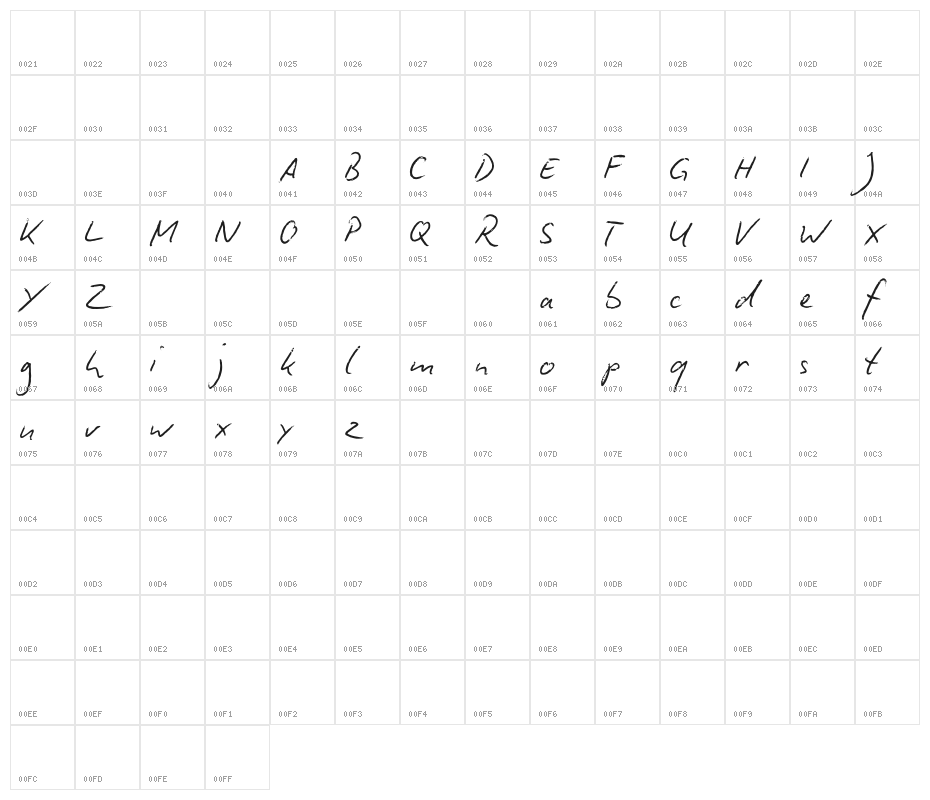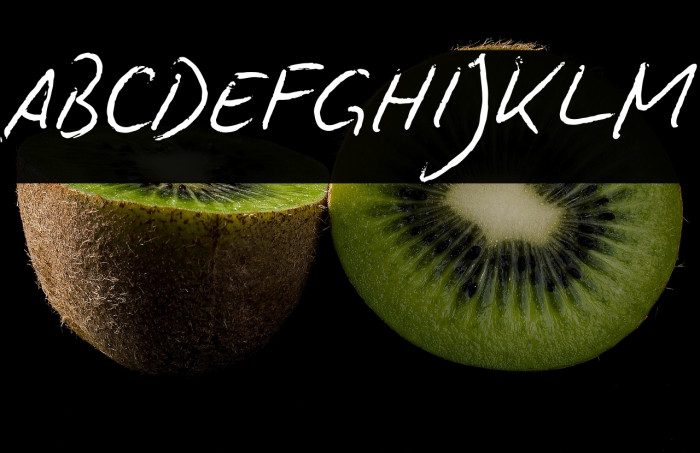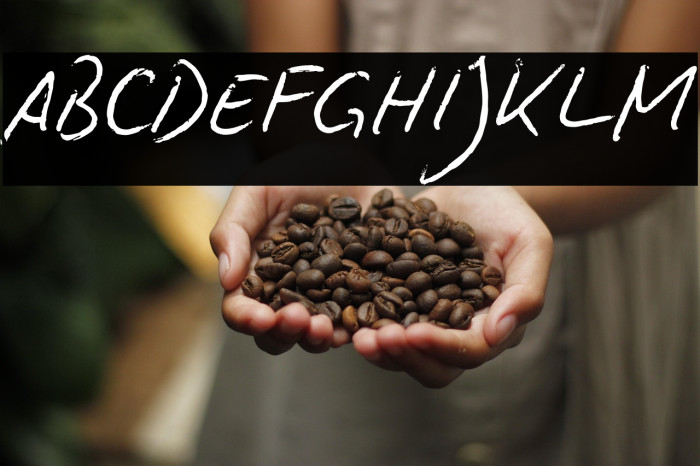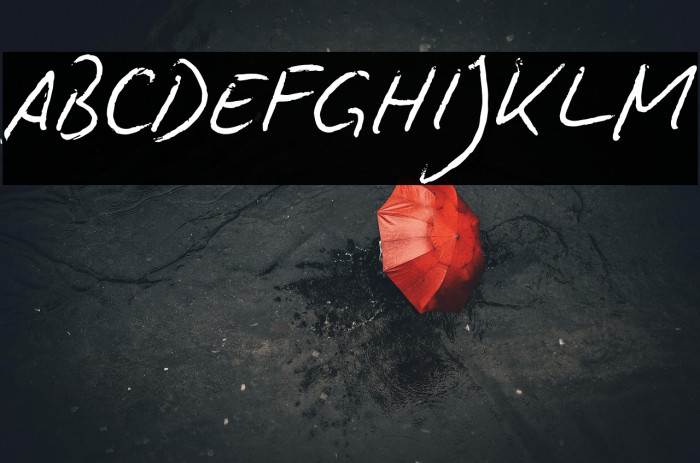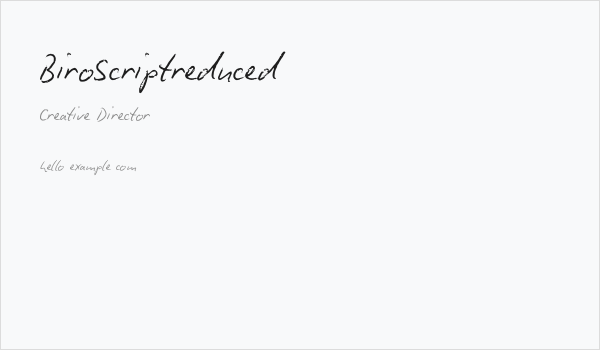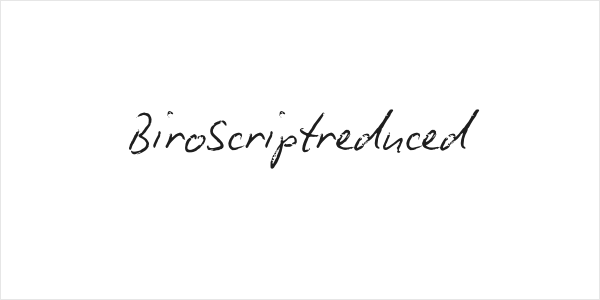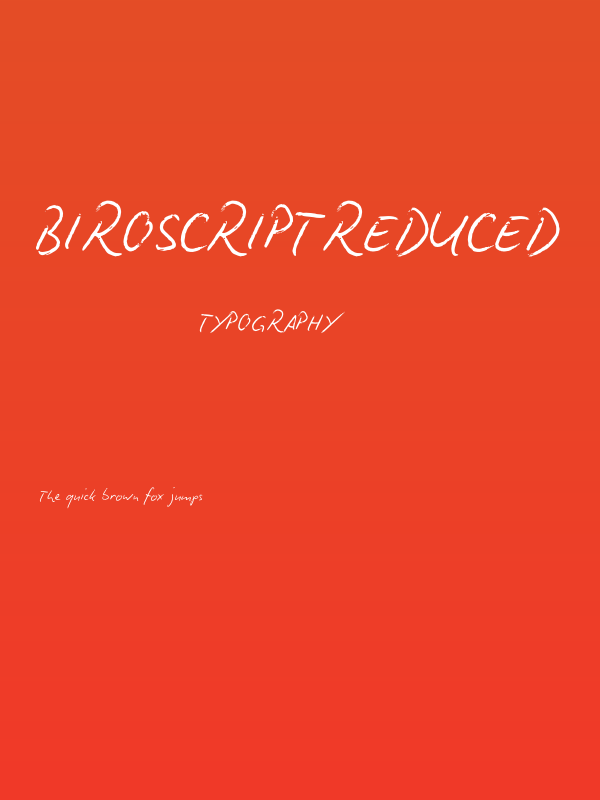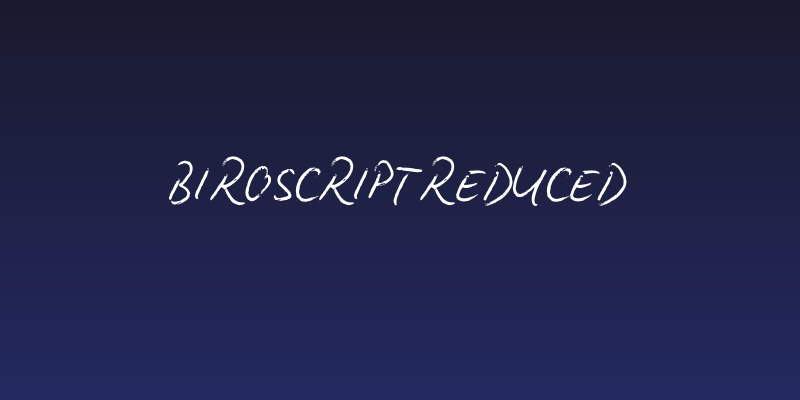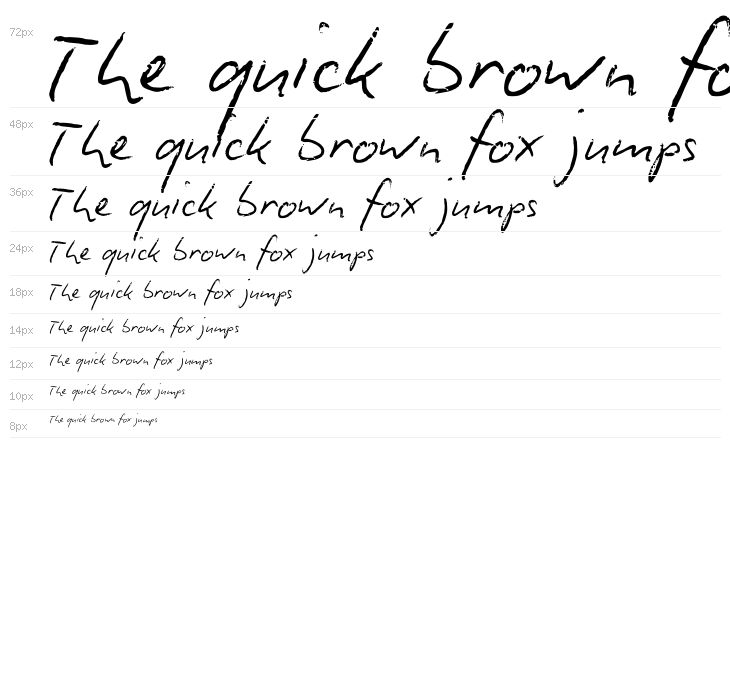
BiroScriptreduced Font
| 分类 | Handwritten |
| 斜体 | Yes |
| 整体风格 | Casual, Artistic |
| 使用场景 | Logos, Invitations, Artistic Projects |
| 推荐项目 | Ideal for personal invitations, artistic branding, creative writing projects, and any design requiring a handwritten touch. |